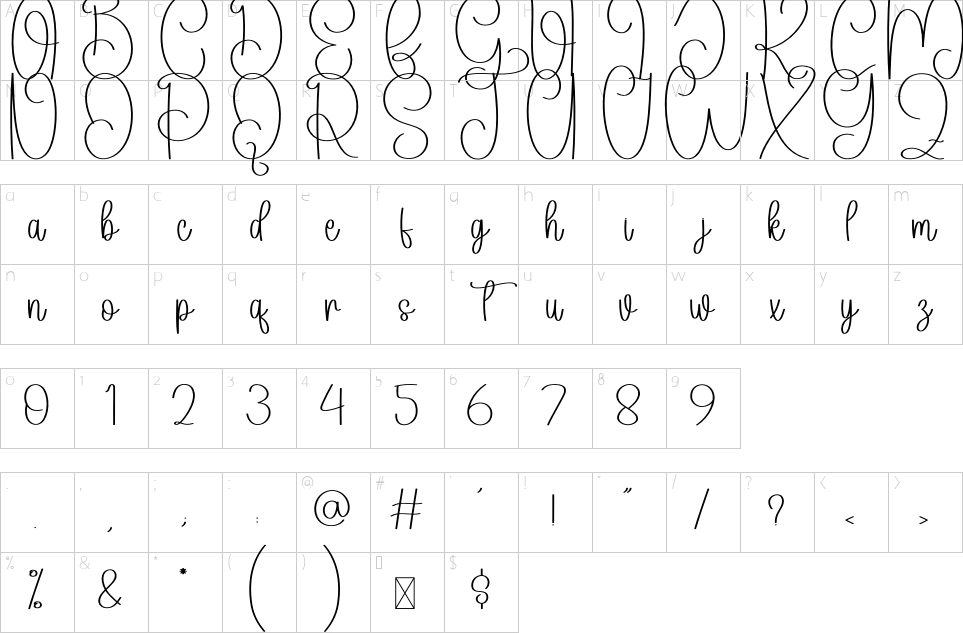
Aqui está uma descrição em português do Brasil para a página de download da fonte ‘Graduation Font – 1001 Free Fonts’, seguindo as instruções fornecidas: Esta é uma fonte semicursiva chamada Graduation, ideal para estilos escolares e graduais. Desenvolvida por scratchones, essa fonte foi projetada com cuidado para se adaptar perfeitamente às necessidades de design do ensino superior. Composta em 104 tipos diferentes que vão desde as letras minúsculas até números e símbolos especiais, a Graduation é uma opção perfeita para quem procura uma fonte moderna e versátil para seus trabalhos escolares ou graduais. Baixe a sua cópia gratuita aqui hoje!